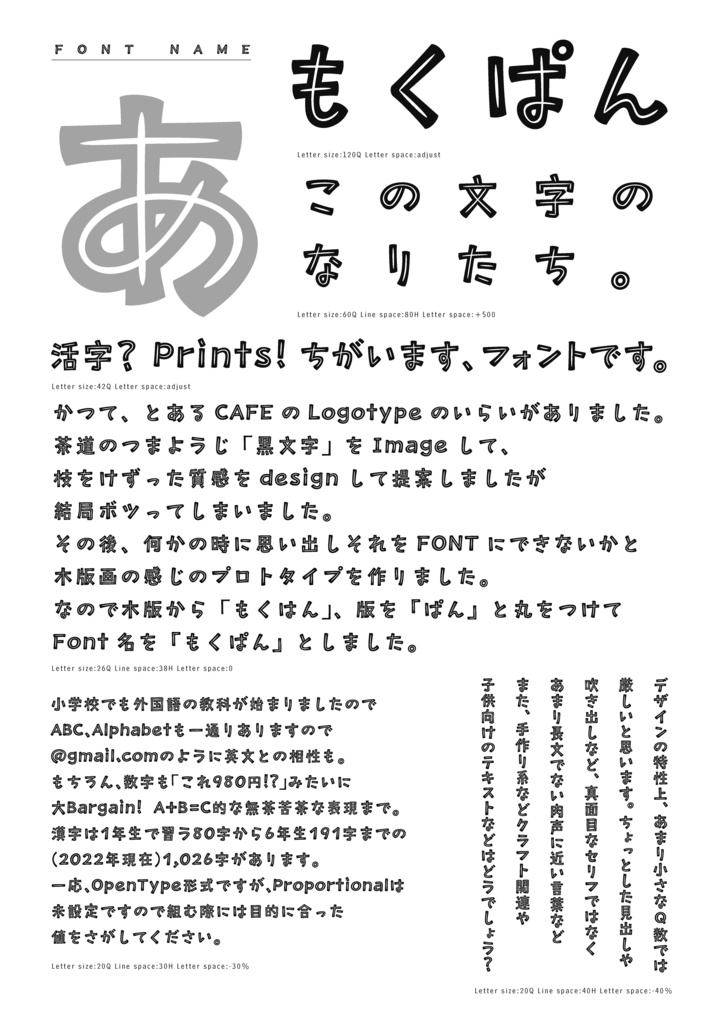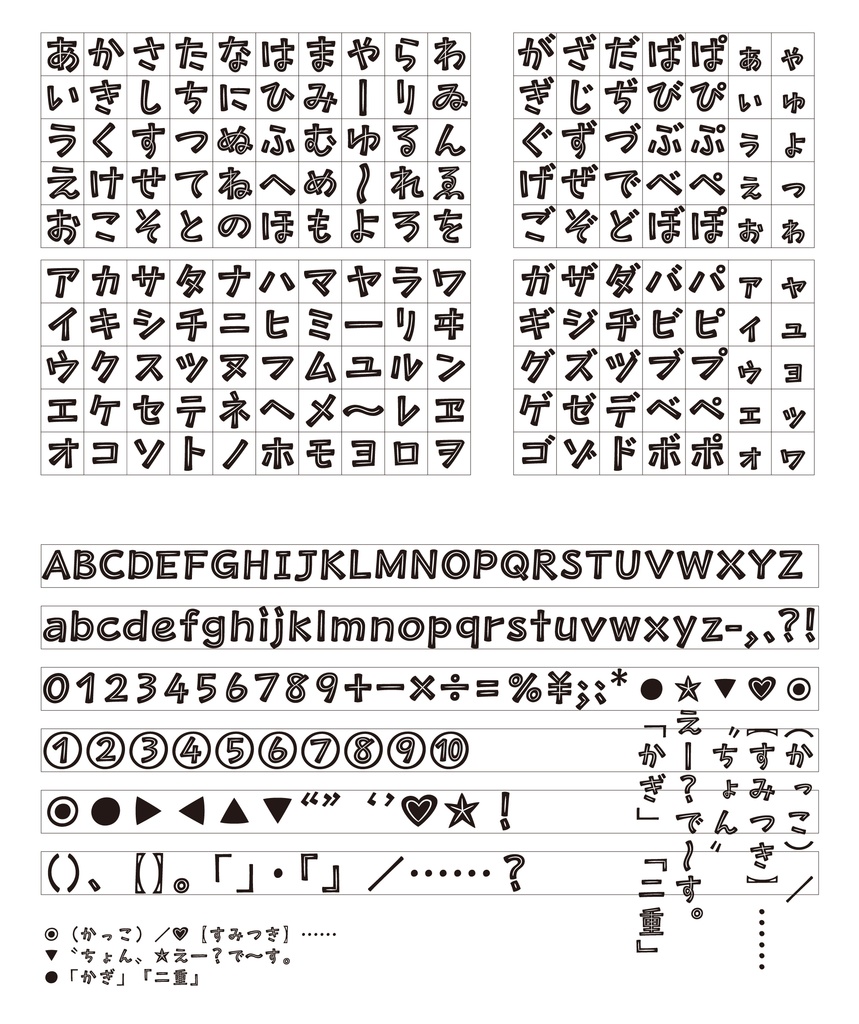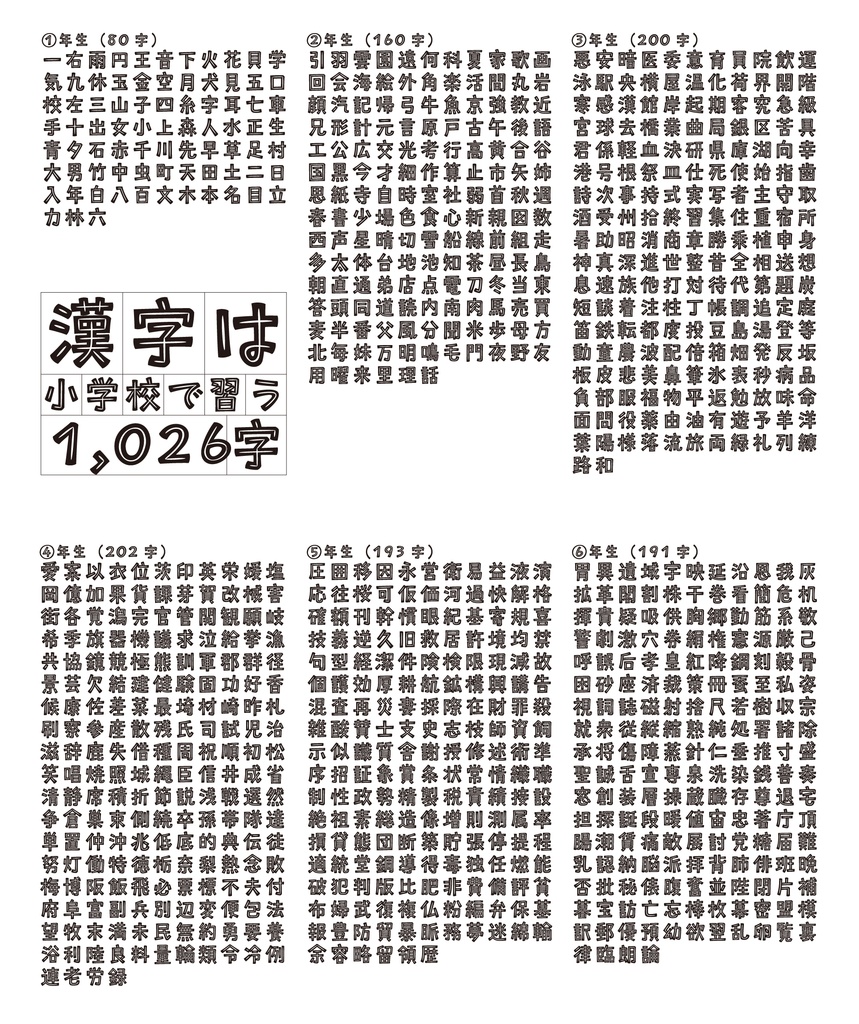
font: もくぱん
木版画のように彫刻刀で彫った(刷った)ようなフォントです。 ひらがな、カタカナ、英数、各種記号と、小学校で習う漢字約1000字のフォントデータです。 あまり小さなサイズは厳しいですが、肉声に近い吹き出しや、手作り系の見出しなどでピッタリだと思います。 フォントに関する以下の使用許諾書をご確認ください。 【仕様許諾】 フォントを購入することで、フォントのデータファイルは 販売されるのではなく 本契約条項にしたがって使用する権利のみ許諾されるものです。 フォントの権利・著作権は書体制作者・G体にあります。 【使用制限】 ご購入いただいた方の権利はコンピュータ1台に対して 1ライセンスをインストールして使用する権利です。 データファイルの一部、または全部を 第三者に譲渡または貸与することはできません。 また、本製品の無断コピー、ストレージ等での共用、 販売、配布、データの改変はいずれも著作権侵害となります。 【責任制限】 フォントの使用により生じた直接的・間接的な損害について は保証、責任は負いません。 【別途契約】 (以下の場合はお問い合わせください) ○社名や商品等のロゴタイプとして商標登録する場合 ○アプリケーション、ゲーム等のソフトでの使用 ※Webフォントには対応していません。 ただしアウトラインデータ(画像)として使用することは可能です。